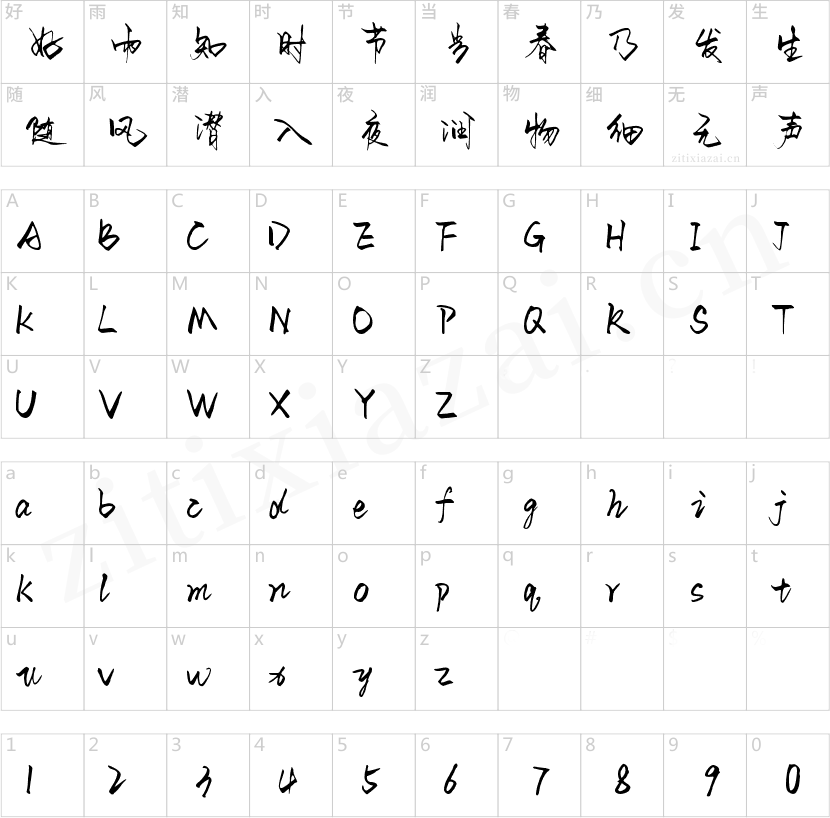
Aa醉里挑灯看剑
Aa醉里挑灯看剑字体
Aa醉里挑灯看剑是一款非常具有艺术性的字体,它的设计灵感来源于对古典艺术的研究,同时又融入了现代字体设计的元素。字形优美,笔画粗细变化自然,给人以大气、典雅的感觉。Aa醉里挑灯看剑是一款既传统又现代的字体,它的设计充满艺术感,美观大方,实用性也非常强。无论是对于设计师还是对于普通读者来说,都是一种非常不错的字体选择。Aa醉里挑灯看剑适合用于具有艺术感的场合,比如海报、宣传单张、书籍封面等。由于其字形流畅且具有动态感,也适合用于大量的文本排版,如报纸、杂志等。